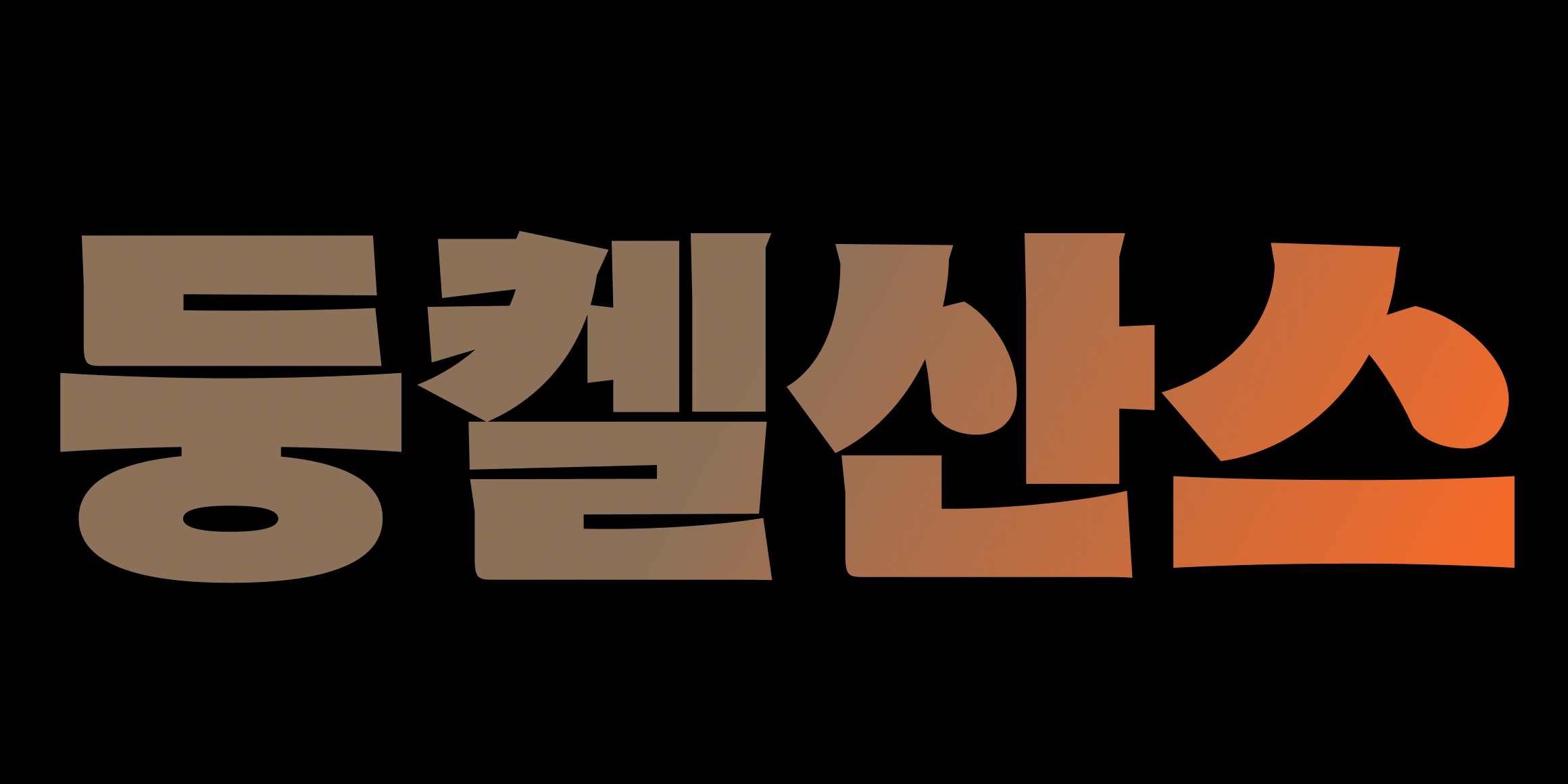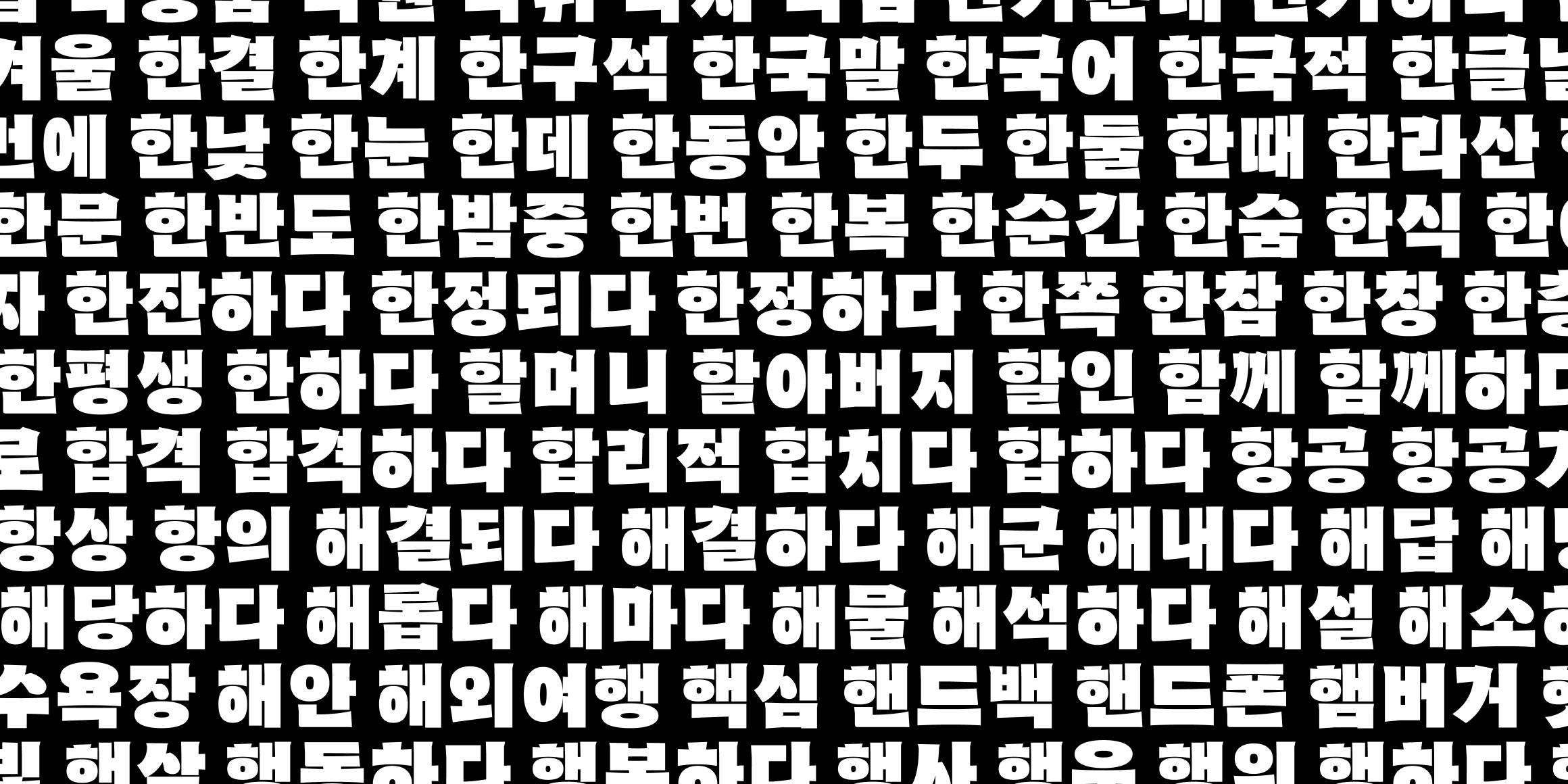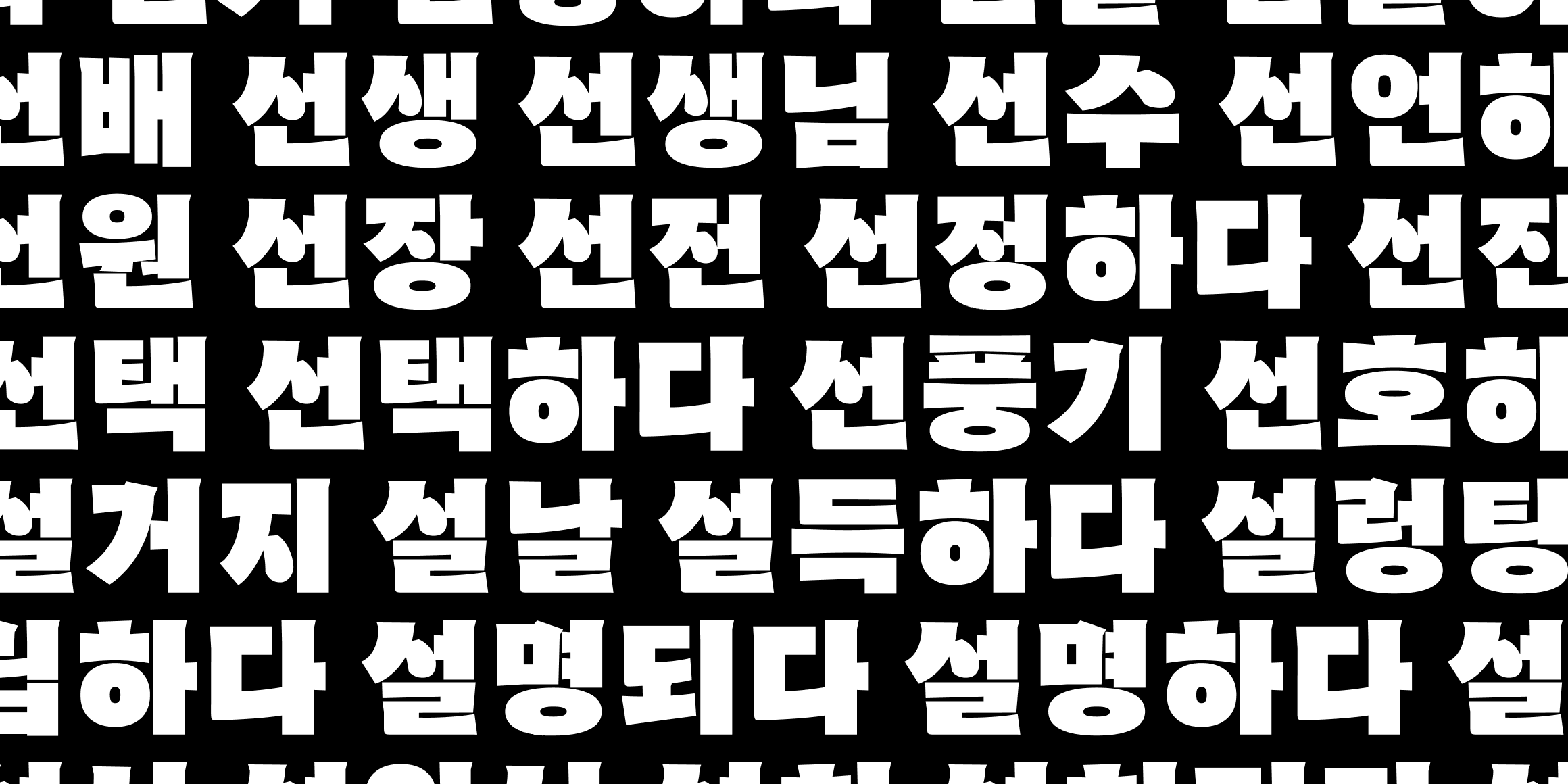
Yoon 하이파이브
Yoondesign
하이파이브는 쭉쭉 늘어나는 유연한 형태의 제목용 서체입니다. 탄력적이고 속도감 있는 획의 표현과 자연스러운 연결성이 특징이며, 발랄하고 활기찬 인상이 느껴집니다. 굵은 굵기로 제작되어 시각적 주목이 필요한 매체에 사용하기 적합합니다.
• 김지연
• Yoon 하이파이브 / Yoon Highfive